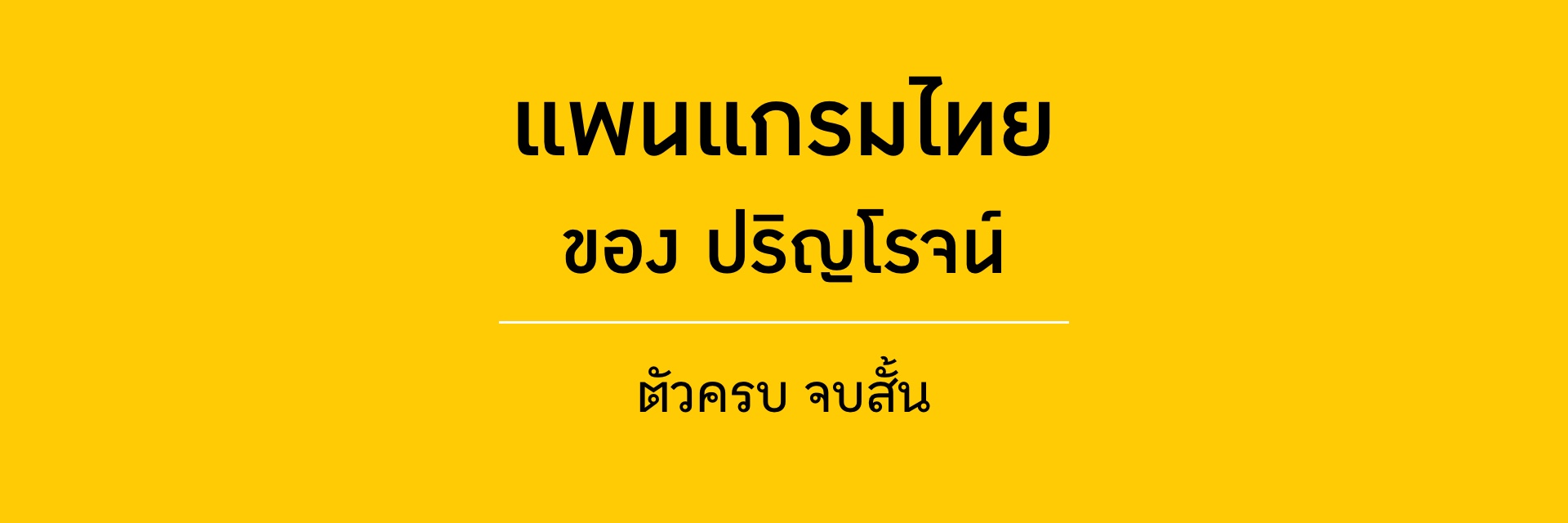
แพนแกรม (pangram) คือข้อความที่ใช้อักษรในภาษานั้นๆ ได้ครบทุกตัว.
English Pangram ที่ใช้กันมากสุด:
The quick brown fox jumps over the lazy dog.
- มี a-z 26 ตัว ครบ จบแค่ 35 พิมพ์.
- แต่ถ้าจะเอา A-Z ด้วย ก็ต้องพิมพ์ซ้ำเพิ่มอีก 35 รวมเป็น 70 พิมพ์.
PrinRoj's Thai Pangram :
ฉันท์ มาฆฌาน
เฒ่าผู้ฝันพลิกฟ้าทฤษฎีปฏิบัติธรรม
เป็นจำอวด ฅนขายฃวดชาโซดา บัณฑิตจุฬาฯ
ฦาถึงเศรษฐีไทย สะใภ้ฮาๆ คือ
หอยจ๊อ ปญฺญาแจ๋ว
- ตัวครบ 71 อักขระไทยที่พิมพ์ได้จากแป้นพิมพ์.
จบสั้น แค่กดพิมพ์เพียง 118 ครั้ง!
หมายเหตุ
- ใช้ประกอบการเรียนการสอน เพื่อฝึกเขียน คัด พิมพ์ อักขระไทยทุกตัวได้ถูกต้องครบถ้วน.
- ใช้ประกอบการเรียนการสอนวิชาออกแบบฟอนต์ไทย เพื่อทดสอบดูทั้งความสวยงามกลมกลืนของกลุ่มอักษรคล้าย และความอ่านง่าย แยกแยะออกระหว่างคู่อักษรสับสนที่เขียนคล้ายกัน (ใน "แพนแกรมไทย ของ ปริญโรจน์" ได้พยายามจัดวางกลุ่มอักษรคล้ายไว้ใกล้ๆ กันอยู่แล้วเพื่อให้ดูเทียบกันได้ง่าย.)
- ใช้พิมพ์ตรวจสอบคุณภาพฟอนต์ในเบื้องต้นก่อนที่จะตัดสินใจนำไปใช้ผลิตสื่อจริง.